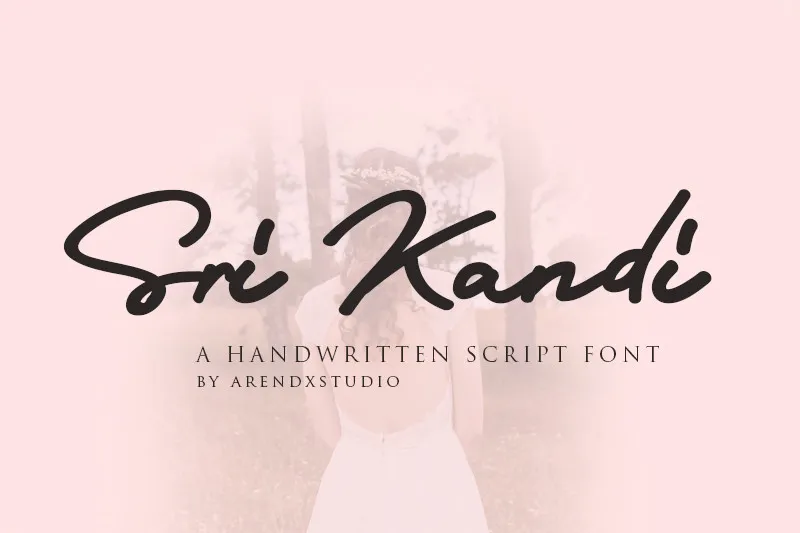
Sri Kandi Script Font é uma elegante e fresca caligrafia handwritten que traz uma pegada contemporânea aos seus projetos de design. Inspirado na autêntica mão do escritor, este estilo único adiciona um toque distintivo a qualquer projeto, tornando-o ainda mais inovador e pessoal. A fonte está disponível em duas formatos: OTF e TTF, facilitando sua fácil integração nos seus projetos. Importante ressaltar que não é necessário qualquer software especial para utilizá-la – basta instalá-la como se faz normalmente no seu sistema de maneira simples e eficiente. Com o Sri Kandi Script Font da arendxstudio, você pode introduzir uma dose de personalidade e modernidade em seus trabalhos. Seja em um poster, um logotipo ou qualquer outro projeto visual, esta caligrafia handwritten oferece a oportunidade perfeita para expressar individualidade ao mesmo tempo que mantém o estilo e a funcionalidade dos designs digitais.
Designer: arendxstudio